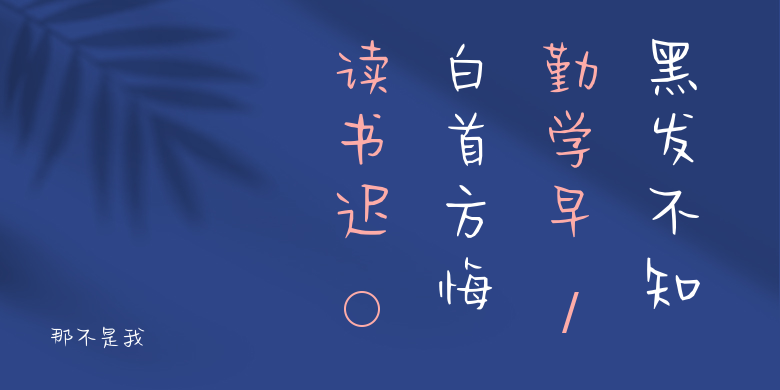
那不是我
那不是我,这款字体结构工整、笔画清晰,兼顾美观与易读性,适用于标题、正文、海报、包装、LOGO 等多种场景。字形优雅稳定,风格百搭耐看,适配日常排版与创意设计,让文字呈现更舒适、更具质感。那不是我一笔一画,皆是细节,以均衡的比例、流畅的线条打造舒适视觉体验,字形端正大气,风格简约现代。无论是商业设计、品牌宣传还是日常排版,都能轻松驾驭,让文字更有格调与力量。那不是我字体下载。